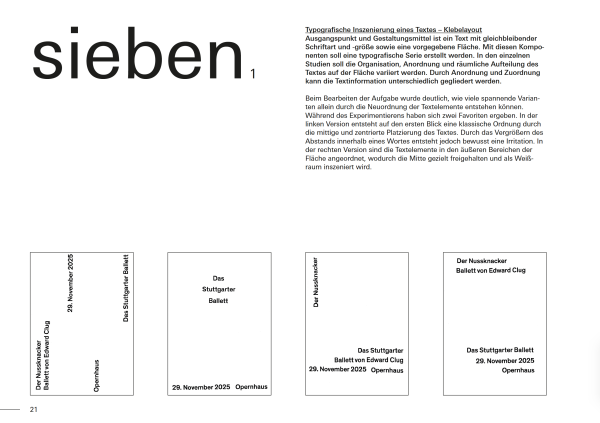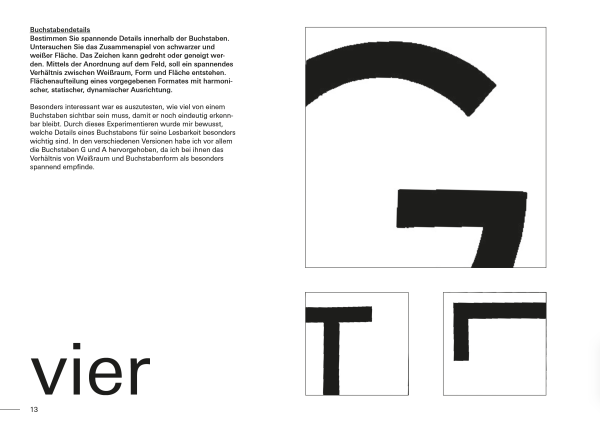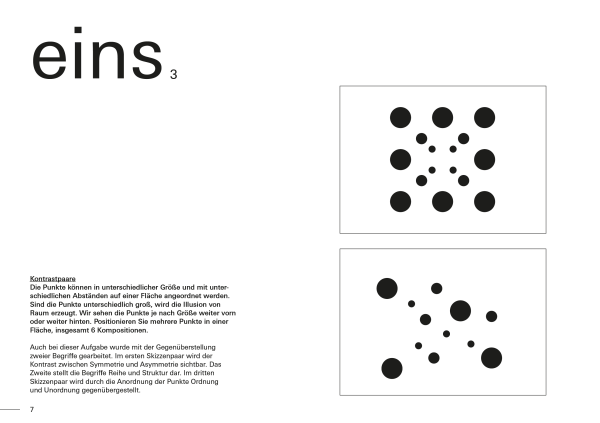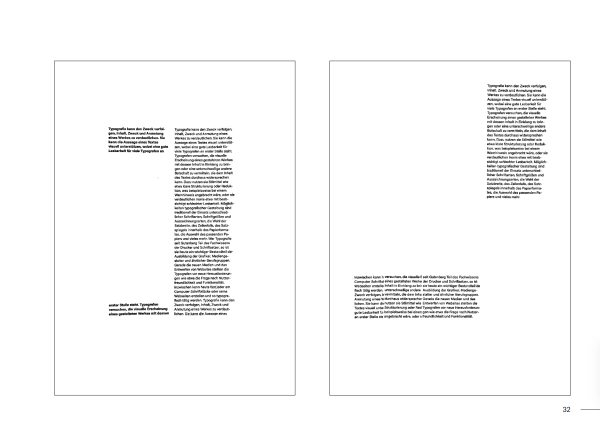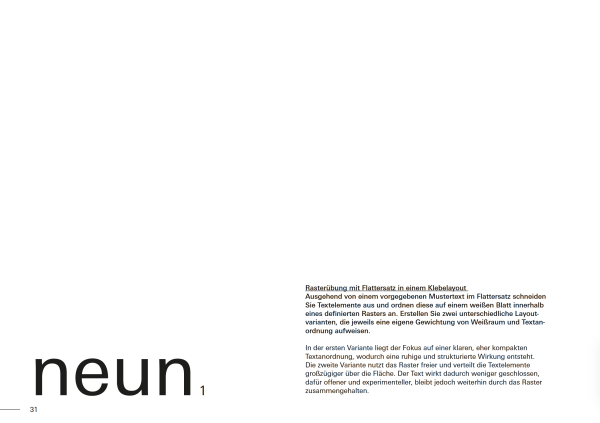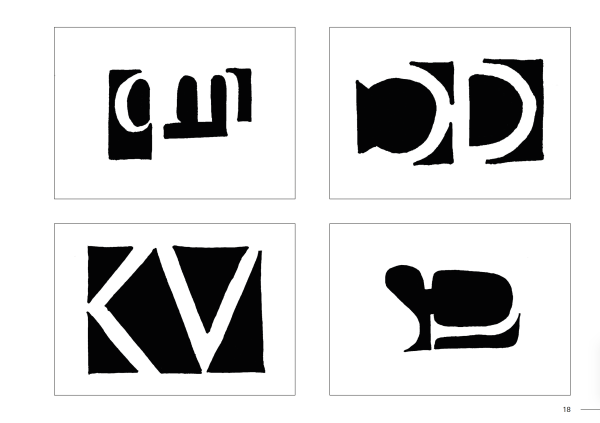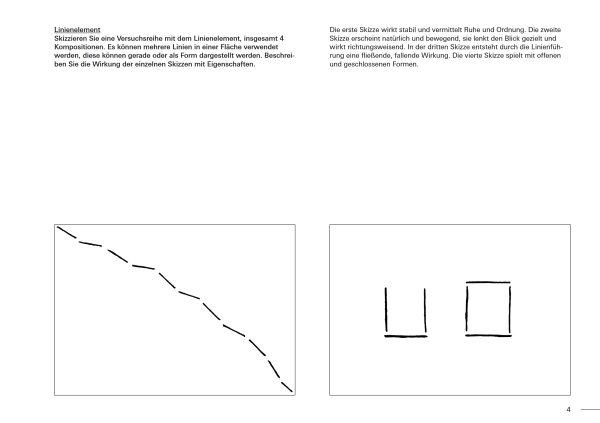
Der Kurs vermittelt die Grundlagen der Gestaltung mit Schrift. Die Studierenden erproben Lesbarkeit, Informationsstrukturierung sowie die Wirkung von Schrift in unterschiedlichen Medien.
Inhalt des Faches
Das Fach Grundlagen der Typografie führt in die mikro- und makroästhetischen Grundlagen der Arbeit mit Schrift ein. Ausgehend vom einzelnen Buchstaben, der kleinsten typografischen Einheit, bis hin zu komplexeren Layoutentwürfen wird der Umgang mit Schrift erarbeitet. In unterschiedlichen Übungen werden formale Fragestellungen zu Form, Gegenform, Proportion, Kontrast oder Rhythmus im Bezug auf die Anwendung und Wirkung unterschiedlicher Schriften von den Studenten und Studentinnen untersucht und besprochen. Im Rahmen eines Kurzprojekts erkunden sie die Möglichkeiten der Typografie als Werkzeug zur Gliederung, Gewichtung und Strukturierung von Informationen.
Die Dokumentation bildet das gesamte Semester im Fach Typografie ab und umfasst alle entstandenen Arbeiten. Sie beinhaltet Übungen, Hausaufgaben, Präsentationen sowie die Entwicklung des Abschlussprojekts. Im DIN A4 Querformat angelegt, macht sie den Arbeitsprozess über die Dauer des Semesters hinweg sichtbar.